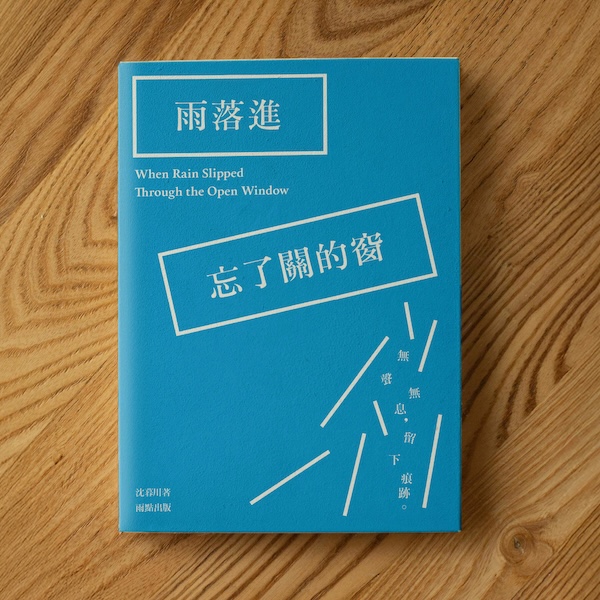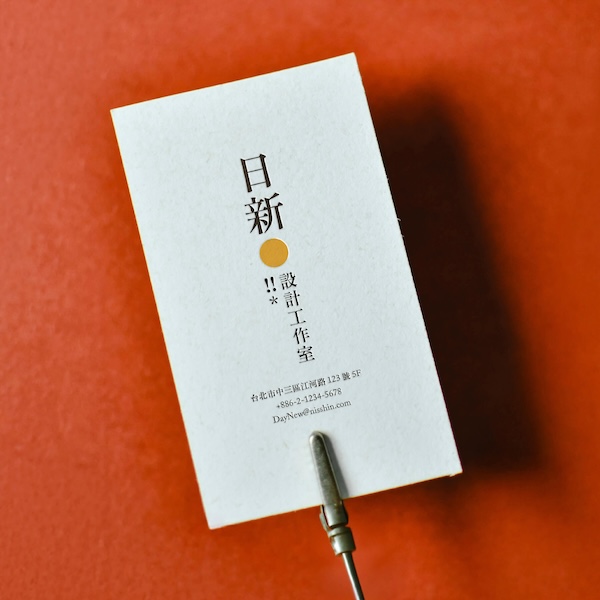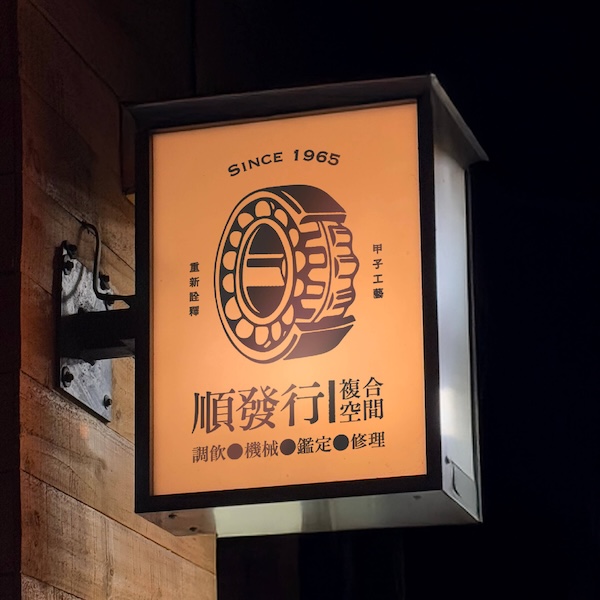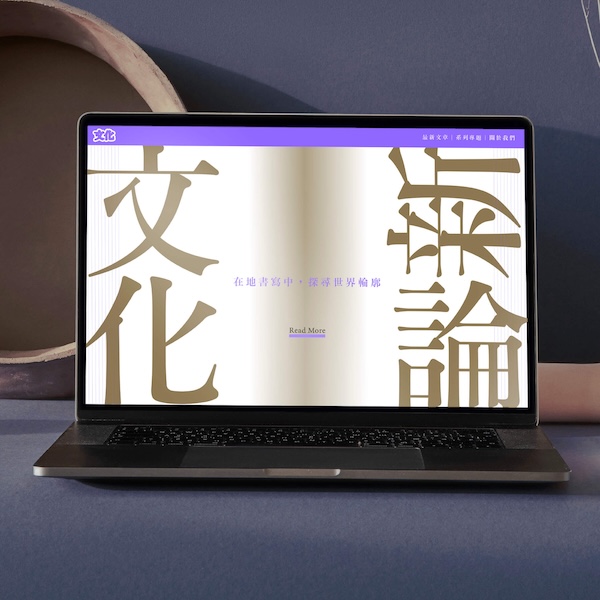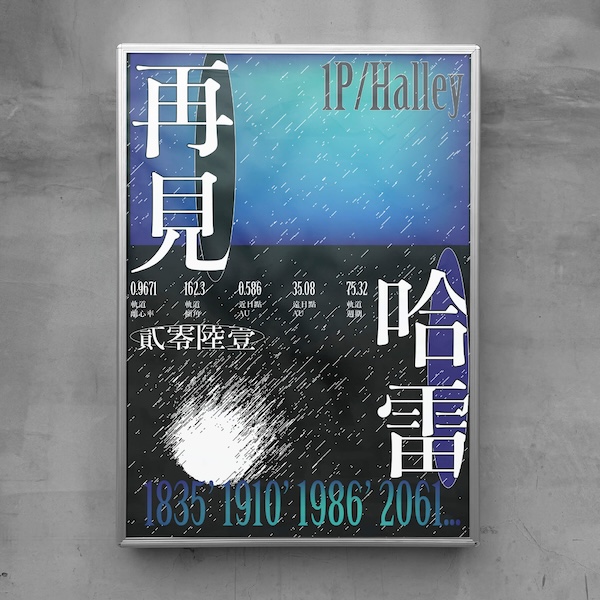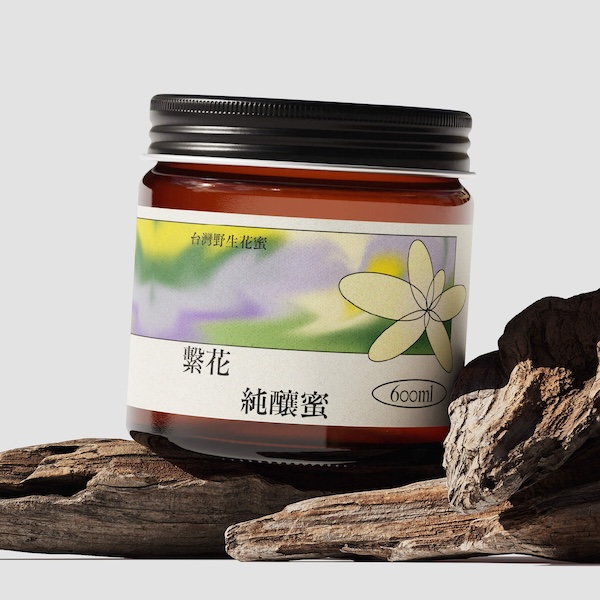
日星宋體貳號
日星鑄字行貳號宋體鉛字銅模修復的數位修復字型。由日星二代老闆張介冠親自以數位方式主力修復。傳承鉛字師傅的手藝,是明體造型的經典風格。平衡易讀,粗細適中適合標題短斷句。帶有印刷傳承造型與書寫筆墨韻味,竪排典雅有文氣,優雅雋永、百看不膩。
日星鑄字行
臺灣最後一家鑄字行,至今仍持續鑄著鉛字。現與臺灣活版印刷文化保存協會合作,致力推廣鑄字、活版印刷文化的復興與保存。